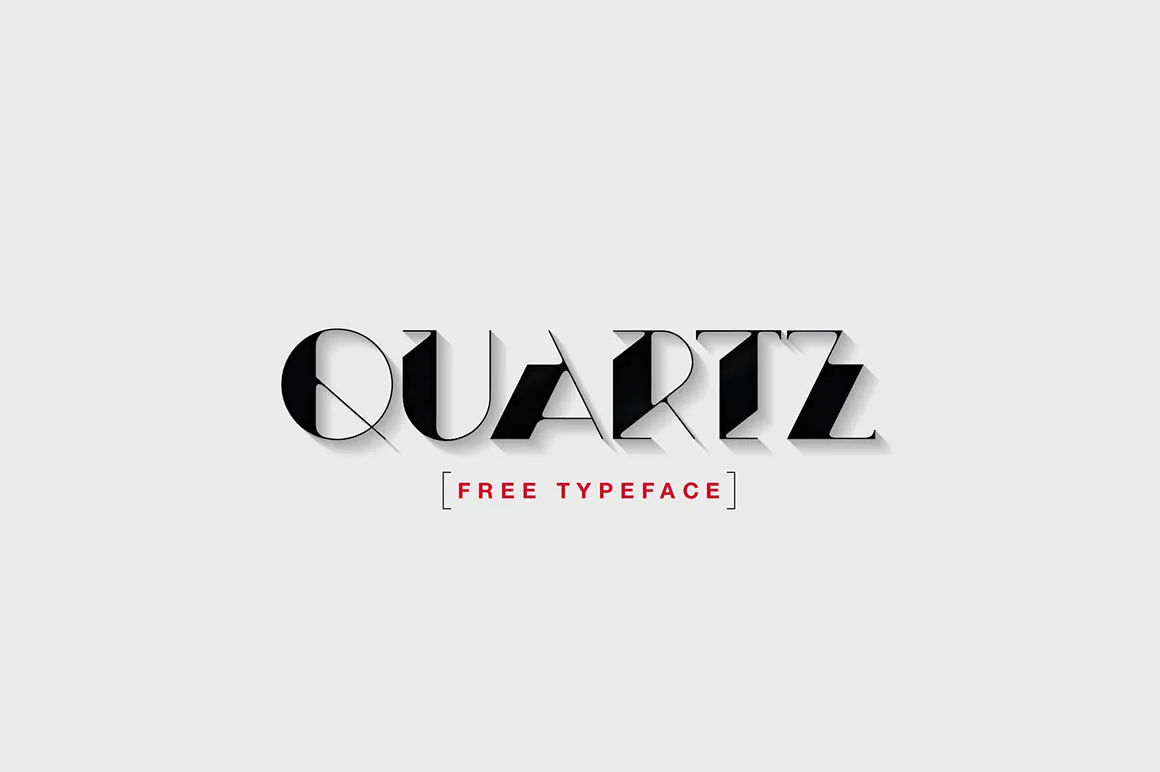
Quartz Font – Fonte Grátis
Quartz Font
A fonte Quartz é uma criação moderna e única desenvolvida por Hamilton. Inspirada no estilo minimalista do design gráfico, essa fonte é perfeita para criar headlines altamente legíveis e estilizadas. Seu arredondamento suave e linhas retas conferem a Quartz um charme distintivo que combina elegância com modernidade, tornando-a uma opção ótima tanto para websites quanto para design de revistas impressas. Se você está procurando por uma fonte moderna que dê uma sensação de frescor ao seu projeto visual, o Quartz é definitivamente um nome a ser considerado. Que tal explorar mais esse estilo moderno e minimalista?